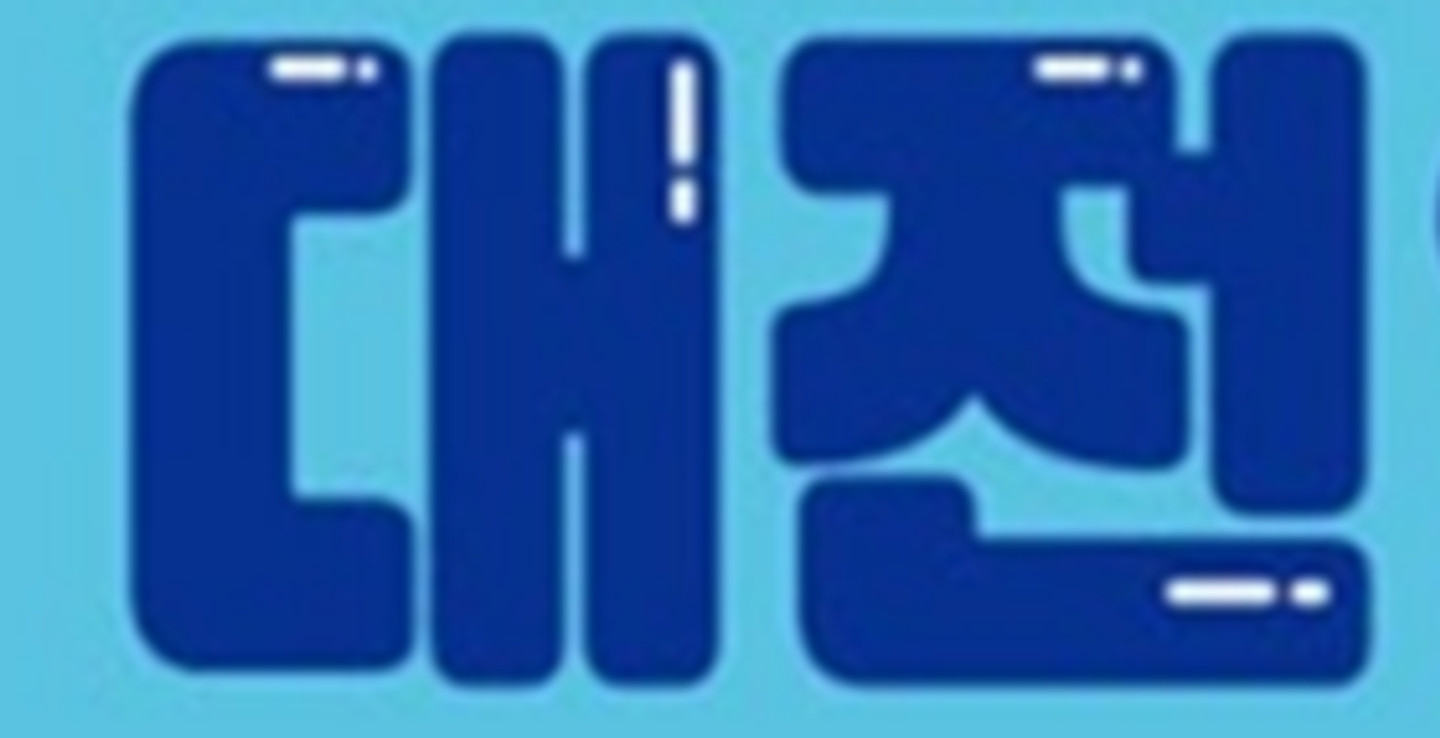
네모 반듯하고 가독성 좋고 세련된 고딕체 추천 부탁드려요! 뭔가 너무 귀엽거나 개성강하거나 정사각이 아닌 고딕말고 좀 정사각이면서 가늘고 굵게 되는 고딕 모두 추천부탁드립니다. 사진에 글씨체도 알려주시면 감사하겠어요~
210옴니고딕
프리미엘 원모어 이벤트 폰트입니다
G마켓
스킨 부스터, 페이스필러 리프팅, 프리미엄 스킨관리, 탄력 리프팅... 폰트입니다. 원스토어 모바일 고딕, 넥슨 Lv.2 고딕, 나눔고딕, 윤고딕, 본고딕 등 다양한 고딕 폰트 활용하시어 제작하시면 될 것 같습니다.